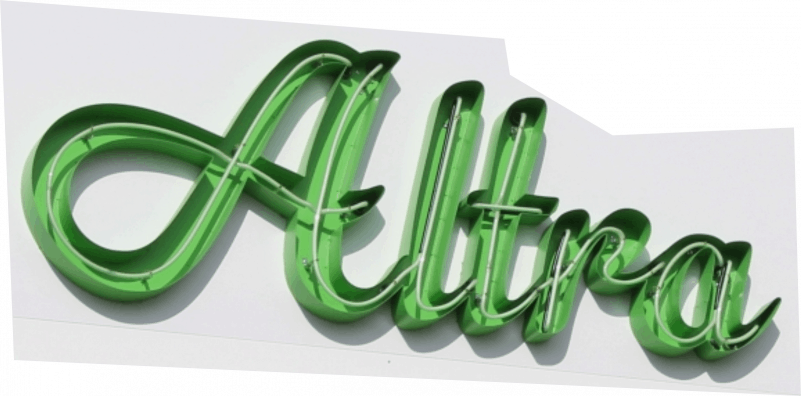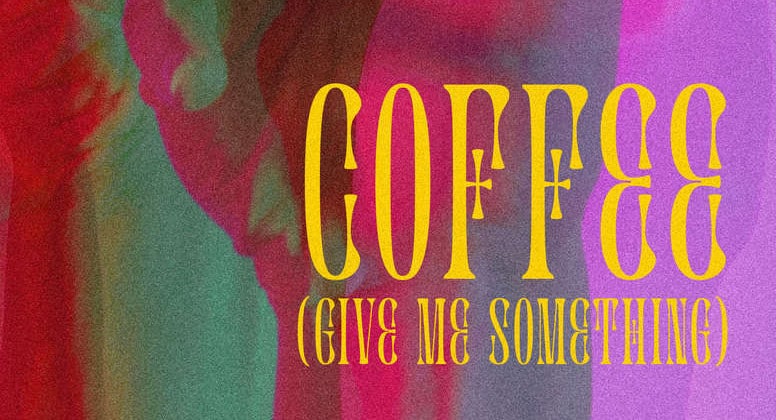
Fonte que está escrito “Doces que encantam”, agradeço
Boa noite, por favor qual é o nome da fonte que está escrito “Doces que encantam”, agradeço
Boa tarde, por favor qual é o nome da fonte que está escrito “Doces que encantam”, agradeço
Boa tarde! Alguém por favor saberia o nome da fonte ” De Repente 40″? Desde já agradeço!
I would love to know the name of the font used for the word CIRCUS.. The font will be too good for a logo design
Necesitaria saber la tipografia que se uso para esta portada de disco
Olá boa tarde, alguém por favor, sabe o nome dessa fonte do nome “Manoel, Nós te amamos!” “50”?! Desde já agradeço.
Qual o nome dessa fonte? Desde já obrigada! 🥰
Boa noite, por favor qual é o nome da fonte que está escrito “Leirielle 12”, agradeço!
Boa noite, por favor qual é o nome da fonte que está escrito “Ter uma irmã”, agradeço
Does anyone know about the font in the picture, because this is very familiar with the font in the picture. Thank you.
Bom dia, por favor qual é o nome da fonte que está escrito “feliz ano novo” “para”, agradeço
Bom dia, por favor qual é o nome da fonte que está escrito “Pablo 23”, agradeço
Boa noite, por favor qual é o nome da palavra que está escrito “Doces que encantam”, agradeço
Bom dia, por favor qual é o nome da palavra que está escrito “Feliz Natal”, agradeço
Bom dia, por favor qual é o nome da fonte que está escrito “Feliz Natal”, agradeço
Hello guys, does anyone know the name of the font used on “Holiday” ?
Hi yall! Would you please help me what this font is? Or some that are similar? A client of mine is being way too stubborn about using this font exactly. I tried looking for some 60/70-ish fonts but none would match. I tried Cooper, Golden Trail… but the squared “A” is driving me insane:___ Btw…
Bom dia, por favor qual é o nome da fonte que está escrito “Projeto Reconectando Saberes”, agradeço
Bom dia, por favor qual é o nome da fonte que está escrito “De” “Para” “Araruna”, agradeço.
Boa noite, por favor qual é o nome da fonte que está escrito “Crisma”, agradeço
Boa noite, por favor qual é o nome da fonte que está escrito “Feliz Natal”, agradeço